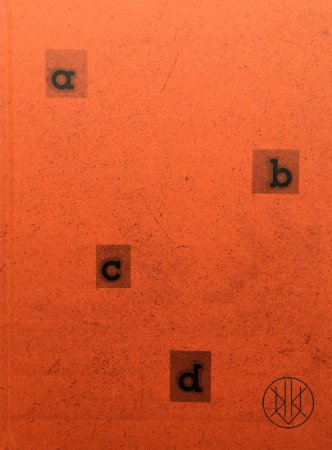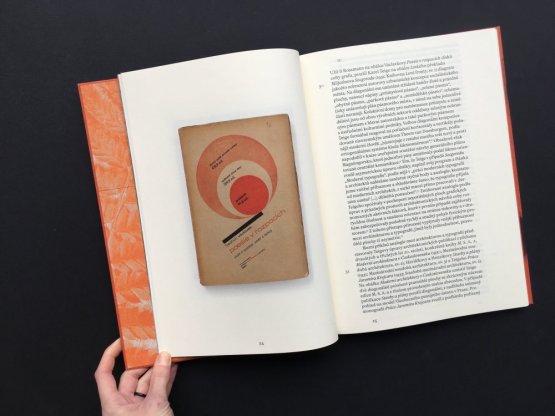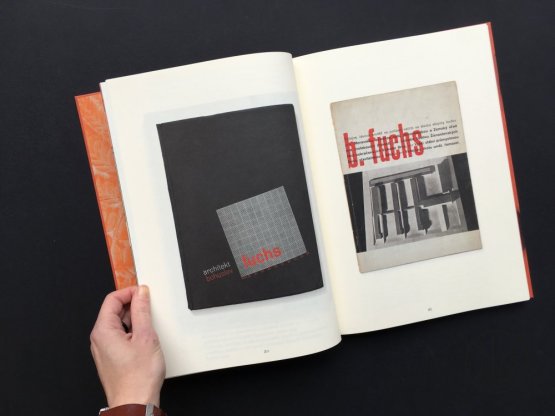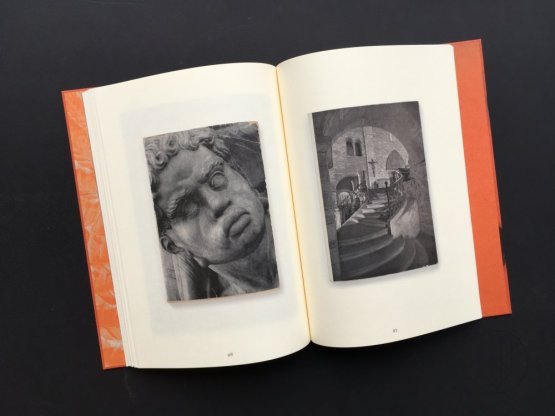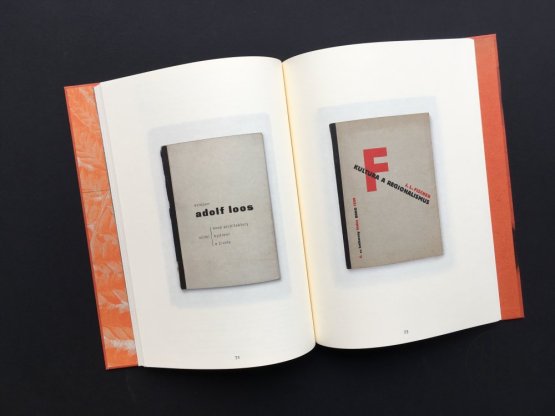
Publikace formou fotografické dokumentace a podrobného komentáře zpřístupňuje nejvýznamnější ukázky funkcionalistické typografie ze soukromé sbírky pedagoga UMPRUM Karla Císaře. Autor tím navazuje na podobně koncipované předešlé monografie Zdeňka Primuse či Johna Vloemanse. Oproti nim se však soustřeďuje výhradně na funkcionalistickou typografii přelomu dvacátých a třicátých let 20. století, od slavného Rossmannova sborníku Fronta přes Teigovy architektonické publikace, Sutnarovy výstavní katalogy a Tschinkelovy didaktické příručky, až po méně známé soukromé tisky Antonína Jera. V katalogu pak zohledňuje především jejich – pro funkcionalismus charakteristické – spojení abstraktních forem s fotografiemi nové věcnosti, které měly vést k vytvoření „nového druhu obrazového písma“. Záměrem publikace není pouze prezentovat izolované knižní obálky, ale také srovnat grafické řešení souborů a sledovat užívání prázdného prostoru, redukci geometrických prvků, použití obrazové statistiky a fotomontážních postupů na obálkách. Kniha není určena jen odborníkům z oblasti dějin grafického designu či dějin moderního umění, ale i ostatním zájemcům o tuto problematiku.
Grafika Petr Bosák, Robert Jansa.
Author Karel Císař
Book design Petr Bosák, Robert Jansa